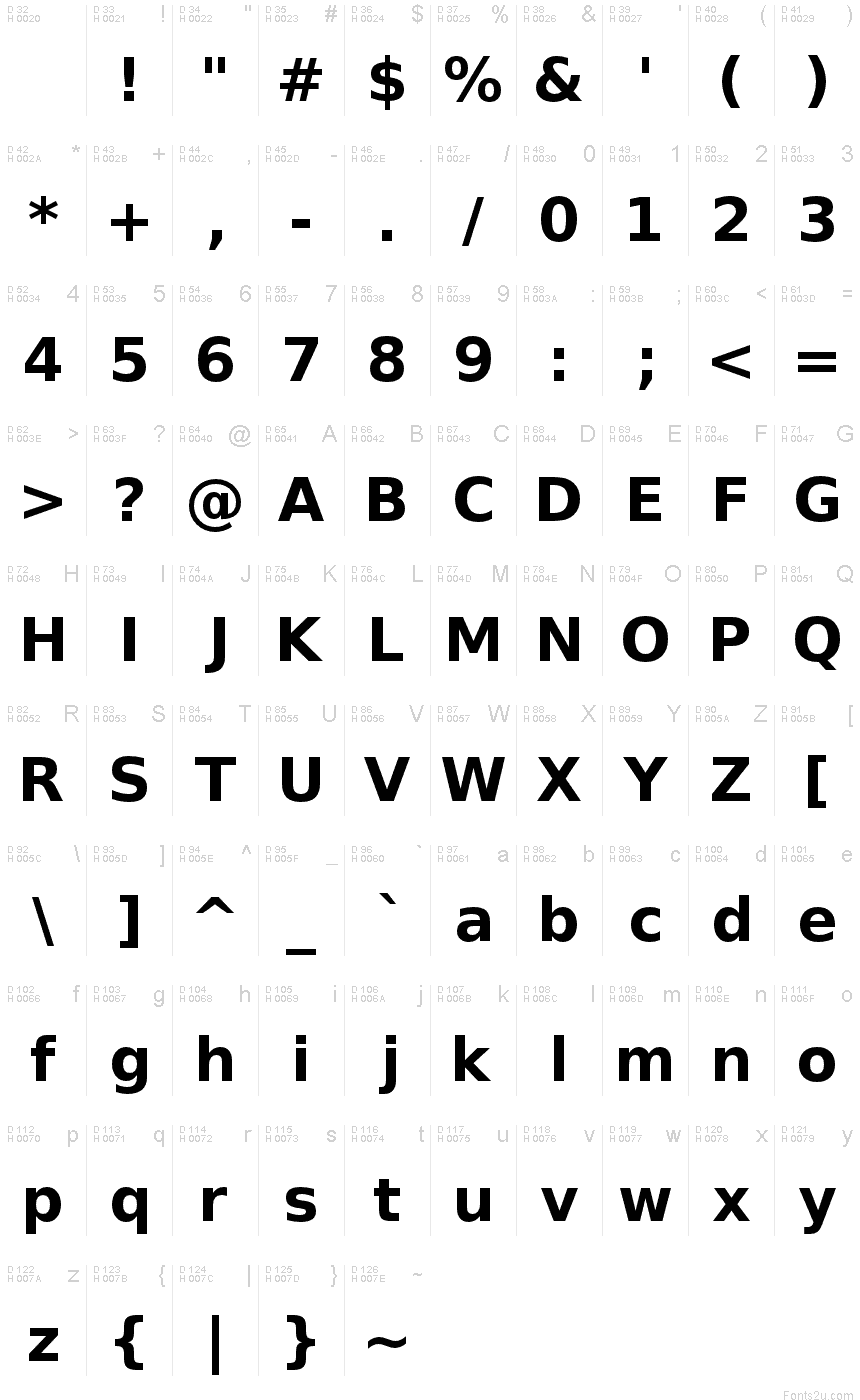
DejaVu Sans Bold, créée par Bitstream et Tavmjong Bah, est une police sans empattement grasse et gratuite, dotée du style moderne et direct des outils de travail pour interfaces. Les lettres sont robustes et sans fioritures, avec des courbes généreuses, des formes ouvertes et une épaisseur compacte qui assurent une texture équilibrée, dégageant une impression de convivialité plutôt que de sévérité.
Elle s'intègre naturellement dans les étiquettes d'interface, les graphismes d'applications, les présentations, les affiches et pour tout branding fonctionnel exigeant une mise en avant claire sans fioritures. En tant que police gratuite, elle fonctionne également très bien pour les titres et les accroches, car son épaisseur solide donne une réelle présence aux mots sans pour autant paraître mécanique.
Glyphes de la police DejaVu Sans Bold — Latin de base, page 1